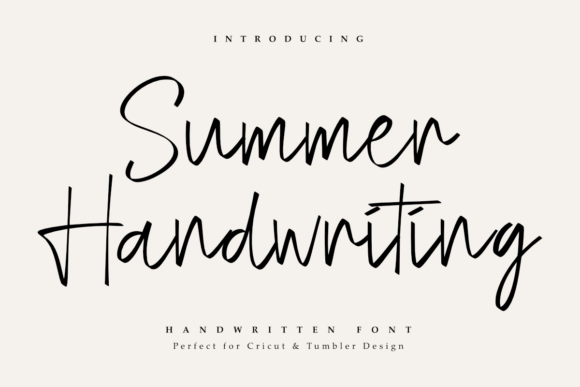
Summer Handwriting
์˜ฌ๋ฐ”๋ฅธ ๋””์ž์ธ ์š”์†Œ๋ฅผ ์ฐพ๋Š” ๊ฒƒ์€ ์–ด๋ ค์šธ ์ˆ˜ ์žˆ์ง€๋งŒ Summer Handwriting๋Š” ์ž‘์—…์„ ์ฆ‰์‹œ ํ–ฅ์ƒ์‹œํ‚ค๋Š” ๋›ฐ์–ด๋‚œ ์ปฌ๋ ‰์…˜์„ ์ œ๊ณตํ•ฉ๋‹ˆ๋‹ค.
์ •๋ฐ€ํ•˜๊ฒŒ ์ œ์ž‘๋œ Summer Handwriting๋Š” ๊น”๋”ํ•œ ๋ฒกํ„ฐ, ๋ถ€๋“œ๋Ÿฌ์šด ํƒ€์ดํฌ๊ทธ๋ž˜ํ”ผ ๋ฐ ์•ˆ์‹ฌํ•  ์ˆ˜ ์žˆ๋Š” ์ƒ์—…์šฉ ๋ผ์ด์„ ์Šค๋ฅผ ์ œ๊ณตํ•ฉ๋‹ˆ๋‹ค.
์ƒํ’ˆ์— ์ „๋ฌธ์ ์ธ ๊ฐ๊ฐ์„ ๋”ํ•˜๊ณ ์ž ํ•˜๋Š” ๊ณต์˜ˆ๊ฐ€, ๊ทธ๋ž˜ํ”ฝ ๋””์ž์ด๋„ˆ ๋ฐ ์†Œ๊ธฐ์—… ์†Œ์œ ์ž์—๊ฒŒ ์ ํ•ฉํ•ฉ๋‹ˆ๋‹ค.